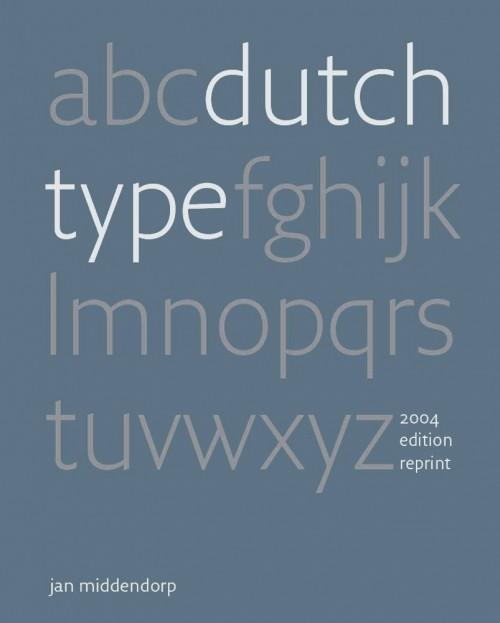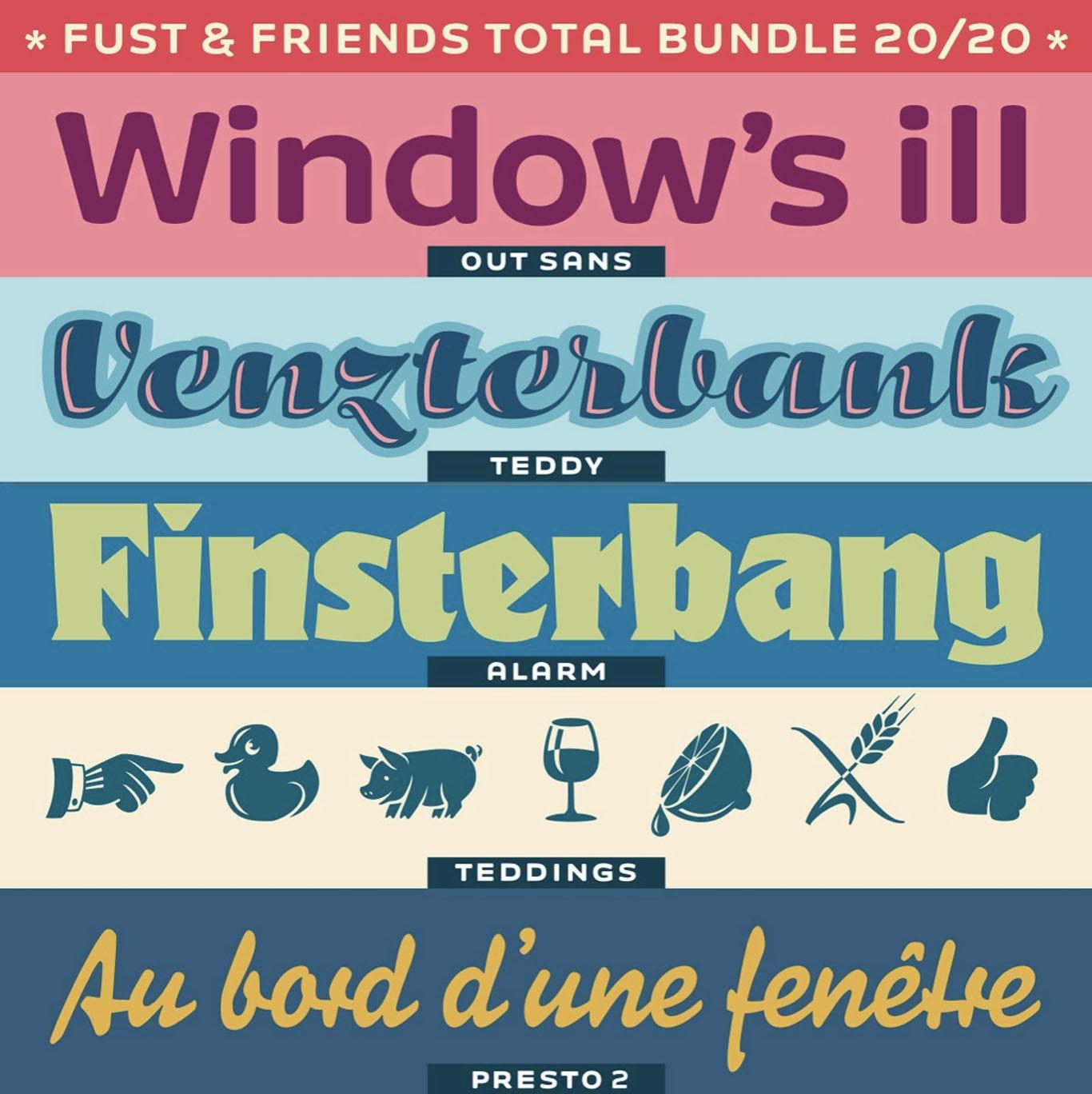
Der Reprint von Jan Middendorps Buch Dutch Type ist ab sofort (und nur in Deutschland und den Niederlanden) für schmale 29,50 Euro erhältlich! Hier gibt es eine Liste mit Bezugsquellen.
Wofür braucht man sowas? Mir fällt gerade keine Anwendung ein, wo ich mir so eine Schrift dringend wünschte :-? Mir wirkt sie sehr aus der Zeit gefallen ...
Ich find sie einfach sehr spannend – unabhängig davon ob ich sie einsetzen kann. Die Wiking, die Ralf gerade digitalisiert, ist ja ähnlich ... beides sehr expressive Schriften aus einer anderen Zeit. Wobei beide Schriften auch damals sicher schon »schräg« waren.
Vorstellen kann ich mir die Alarm überall dort wo es um die Zeit geht aus der sie kommt. Aber auch darüber hinaus finden sich sicher Anwendungen – auf der Website zur Entstehungsgeschichte gibt es auch einige Beispiele.
Die Beispiele habe ich gesehen und mehr als ›überall dort wo es um die Zeit geht aus der sie kommt‹ konnte ich mir auch nicht vorstellen – kommt  bei mir aber ... äh ... so gut wie nie vor ...
Deswegen verstehe ich nicht, dass du sie quasi als must have dargestellt hast (habe ich zumindest so verstanden).
Open your mind! :rockon:
Sie enthält zwar nicht das für mich normalerweise obligatorische Versal-Eszett, aber dafür in allen Schnitten Zahlen, die in einem Kreis sitzen, mit weißer und mit schwarzer Füllung. Solche Fonts gibt es ja eigentlich genug, aber bisher kenne ich nur eine, die nicht bei 10 aufhört, sondern bis 20 geht, nämlich die Lato. Und die Gravitica macht nun erst bei 99 Schluss.